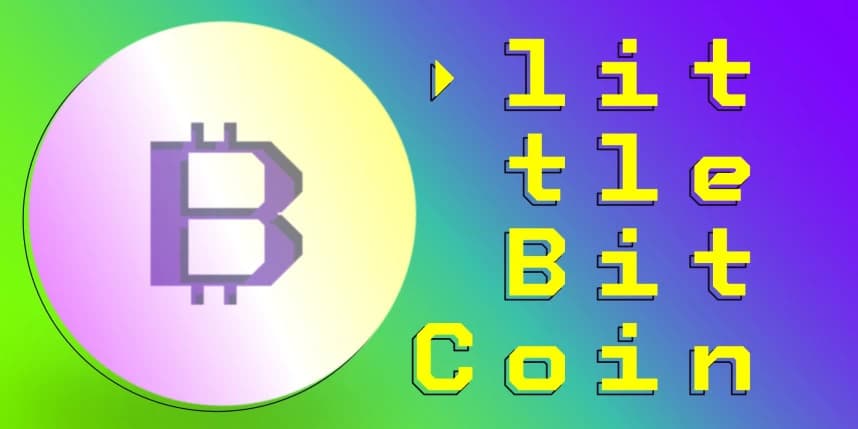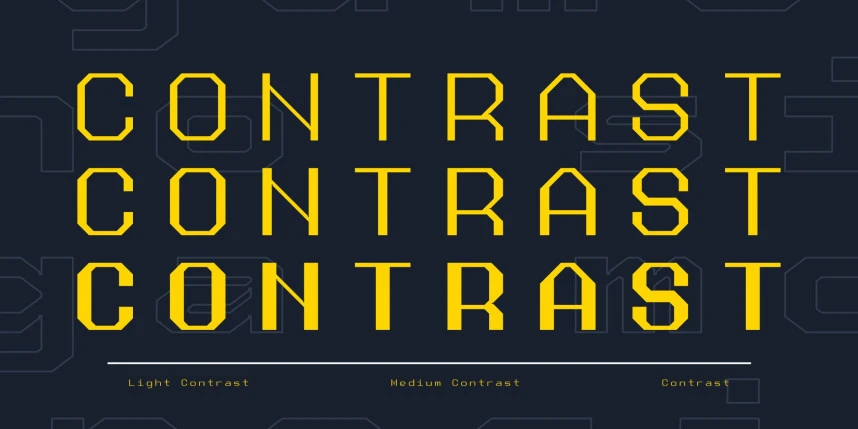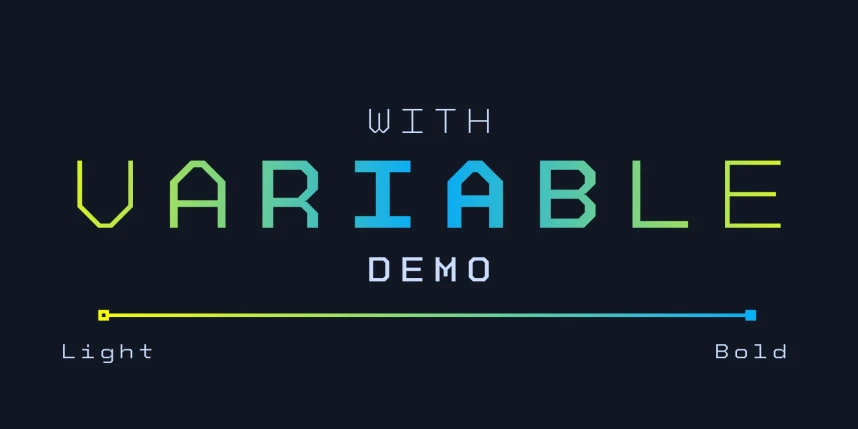
Siga Mono Font
Siga Mono, tüm yaratıcı ihtiyaçlarınız için nihai yazı tipi ailesi. Dijital ve basılı projelerinizi, Siga Mono'nun dikkat çekici monospace düzeni ve özgün stiliyle başyapıtlar hâline getirin.
Siga Mono, tüm yaratıcı ihtiyaçlarınız için en iyi font ailesi. Dijital ve basılı projelerinizi kayda değer monospace düzeni ve belirgin stiliyle başyapıtlar haline dönüştürün.